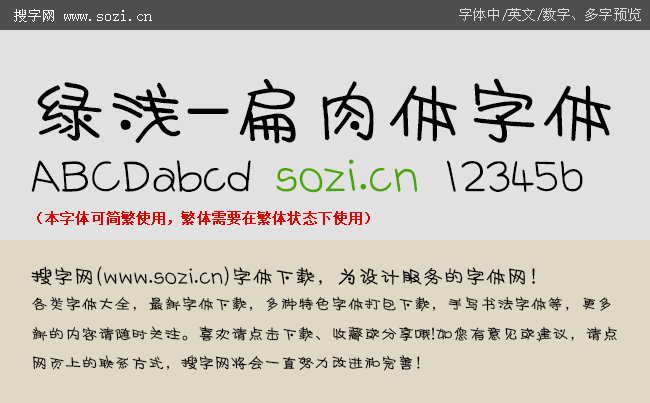
扁肉體字體
扁肉體字體是由搜字網(wǎng)提供中文字體下載,扁肉體字體的字形由pop字體加上可愛的小圓點(diǎn),非常適用于可愛風(fēng)或非主流方面作品設(shè)計(jì),比如廣告設(shè)計(jì)字體、網(wǎng)頁設(shè)計(jì)字體、包裝設(shè)計(jì)字體、 屏幕顯示字體等,歡迎下載哦!